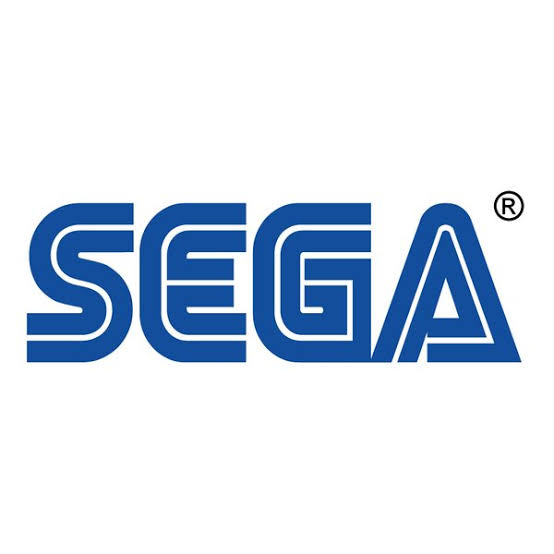
20+ Download Font Keren untuk Logo Terbaru – Dalam hal mendesain logo, pemilihan font merupakan hal yang sangat penting. Pemilihan jenis font dapat mempengaruhi kesan dan karakter dari brand yang Anda buat logonya. Seyogyanya Anda memilih font yang benar-benar cocok untuk brand Anda.
Dikutip dari Berkode.com, terdapat banyak sekali tipe dan macam font. Ada tipe serif, sans serif, display, handwritten (tulisan tangan), script, retro, typewriter, dan masih banyak yang lain.
Apa font yang paling pas untuk desain logo? Semuanya lagi-lagi tergantung pada brand Anda dan karakter apa yang ingin Anda buat.
#1 – Carlito
Font yang simple, clean, tidak kaku, namun tanpa menghilangkan kesan profesional.
#2 – Good Times
Kemudian kami rekomendasikan font bernama Good Times untuk Anda.
#3 – Konigsberg
Font selanjutnya, Konigsberg yang ber-style eropa.
#4 – Clementine Sketch
Anda menggemari font berjenis sketch? Clementine Sketch sepertinya cocok untuk Anda.
#5 – Roadway
Anda pasti sudah tidak asing dengan style font satu ini. Font yang cukup sering digunakan orang-orang untuk menekankan kesan tegas dan klasik.
#6 – Padaloma
Padaloma hadir untuk Anda dengan style bold, regular, dan italic.
#7 – Gavabon
Kembali dengan style sketch, kali ini kami berikan font Gavabon untuk Anda. Yap, download font keren logo satu ini gratis!
#8 – Vtks good luck for you
#9 – Hot Pizza
Anda ingin membuat logo makanan? Font satu ini sangat bisa Anda pertimbangkan.
#10 – Waltograph
Cukup familiar dengan desainnya kan? Font satu ini sangat mirip dengan yang digunakan di logo Walt Disney.
#11 – Deftone Stylus
#12 – Scream Real
Font dengan kesan modern namun tidak meninggalkan kesan tegas dan rapi.
#13 – Hemi Head
Anda penggemar Nascar? Font satu ini sering digunakan oleh tim balap Nascar untuk ‘mencoret-coret’ mobil mereka. Cukup menarik menurut kami.
#14 – SF Sports Night
Font selanjutnya ini bisa Anda pertimbangkan untuk membuat logo bertema olah raga atau sports.
#15 – Hursheys
Hursheys menurut kami cocok untuk dijadikan font produk apparel dan semacamnya.
#16 – Folks-Light
Selain untuk Logo, Folks light bisa Anda manfaatkan sebagai font heading di dalam konten desain.
#17 – Perspective Sans
Perspective Sans diciptakan untuk Anda yang tidak neko-neko dan pencinta minimalis.
#18 – Viking Stencil
Ingin yang sedikit berbeda? Viking Stencil patut Anda coba di dalam project desain.
#19 – Zrnic
Font keren untuk desain logo ini tersedia di dalam 6 style. Mantap!
#20 – Logoblogo 2
Beberapa kali kami melihat logo dengan font demikian. Akhirnya kami menemukan nama font ini adalah Logoblogo.
#21 – Goca Logotype Beta
#22 – Sega
Bila Anda gemar bermain game, sudah pasti kami tidak perlu menjelaskan lebih panjang. Hehe. Anda bisa download font keren dan gaul untuk logo ini gratis.
#23 – Lunch Time